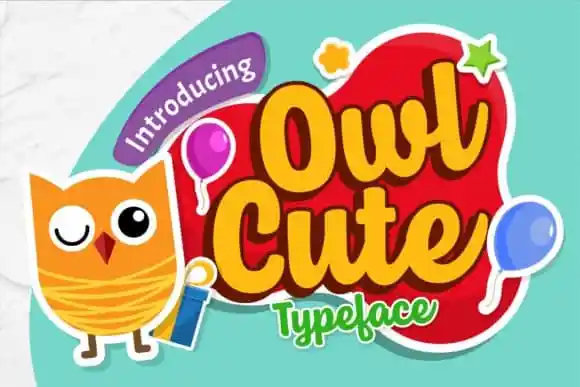
Owl Cute Script Font – Download Grátis
Owl Cute Script Font é uma tipografia alegre e bold perfeitamente adequada para ocasiões infantis e eventos veraneantes. Suave e luminosa, esta fonte tipo display traz um toque encantador às suas criações. É perfeita para desenhos relacionados a crianças e festas de verão. Se apaixone pelo Owl Cute e deixe seus projetos brilharem! Esta fonte é uma ótima escolha para aqueles que buscam algo divertido, suave e vibrante em seu próximo projeto gráfico.